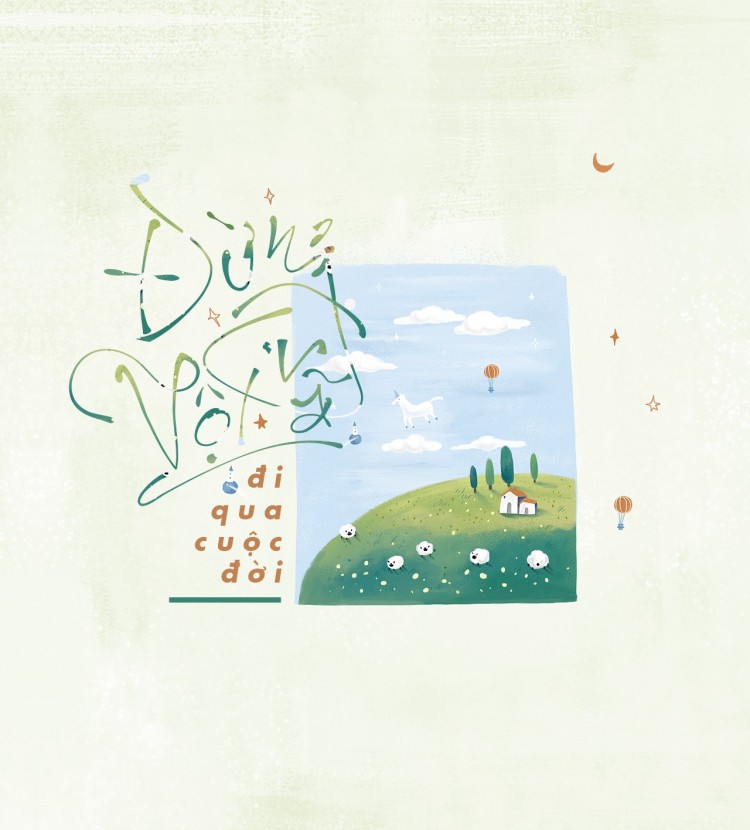
Font việt hóa MTD Second Lyrics
Trong cộng đồng thiết kế đồ họa tại Việt Nam, việc tìm kiếm một Font Miễn Phí chất lượng để làm phụ đề là điều vô cùng quan trọng. Font việt hóa MTD Second Lyrics nổi lên như một sự lựa chọn hàng đầu cho những ai yêu thích phong cách trẻ trung và hiện đại. Đây là bộ phông chữ được tối ưu hóa hoàn toàn cho bảng mã tiếng Việt, giúp người dùng không còn lo lắng về lỗi hiển thị ký tự hay mất dấu khi soạn thảo nội dung sáng tạo.
Đặc điểm nổi bật của Font việt hóa MTD Second Lyrics
Thiết kế thanh thoát và nghệ thuật
Bộ phông chữ này sở hữu những đường nét uốn lượn mềm mại, mang lại cảm giác nhẹ nhàng và đầy cảm xúc cho người xem. Đặc biệt, nó cực kỳ phù hợp để sử dụng trong các video Lyrics trên YouTube hoặc TikTok, nơi mà sự hài hòa giữa phần nhìn và phần nghe cần được chú trọng tuyệt đối. Với độ dày nét vừa phải, phông chữ đảm bảo tính dễ đọc ngay cả trên nền hình ảnh có độ chi tiết cao.
Tính ứng dụng linh hoạt trong học tập
Không chỉ dành riêng cho biên tập video, các bạn học sinh và sinh